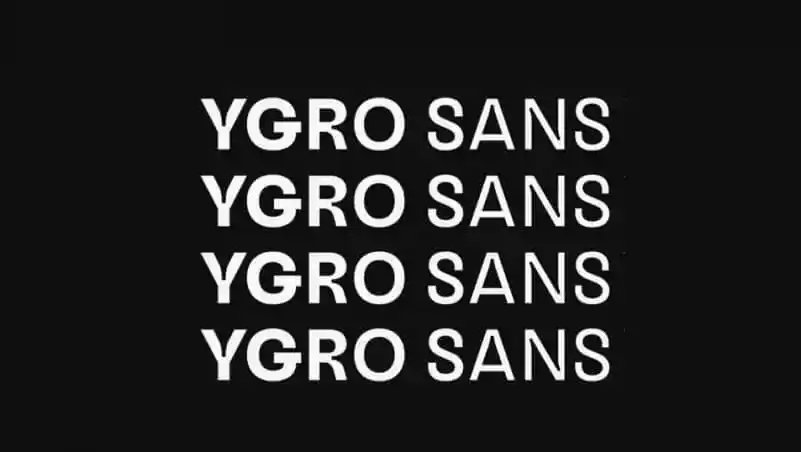
Ygro Sans Serif Font Family – Fonte Grátis
Ygro Sans Serif Font Family
A Ygro Sans Serif é uma fonte moderna que combina elementos serifados clássicos com linhas geométricas e características grotescas para criar um estilo vintage inovador. Esta fonte é versátil, adaptando-se perfeitamente tanto em grandes quanto em pequenos tamanhos de texto. Com seu fundo geométrico sóbrio, pedigree grotesco elegante e tonalidade leve e divertida, ela se destaca como uma escolha ideal para designers que buscam um texto clean, moderno e versátil. Perfeita tanto para uso em sites quanto em materiais impressos, a Ygro Sans Serif é uma excelente opção para quem busca um estilo único e sofisticado. Descubra por si mesmo o charme desta fonte inovadora.